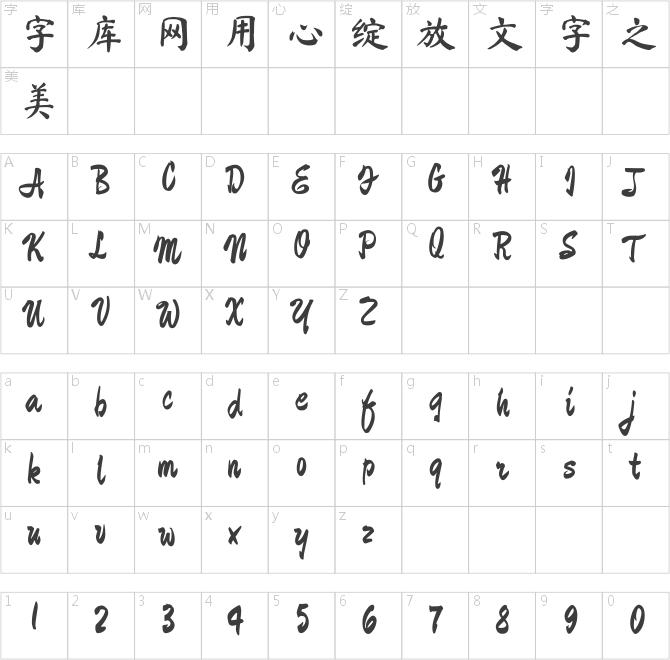
鐘齊馬善政毛筆楷書 詳情頁
字體名稱: 鐘齊馬善政毛筆
鐘齊馬善政毛筆楷書
鐘齊馬善政毛筆楷書字體字庫是一款讓人賞心悅目、百看不厭的中文字體,適合各類廣告和產(chǎn)品包裝設(shè)計應(yīng)用,字體大小5.6MB,格式為ttf字體,上傳用戶是小籃子,作者/版權(quán)方為鐘齊字庫